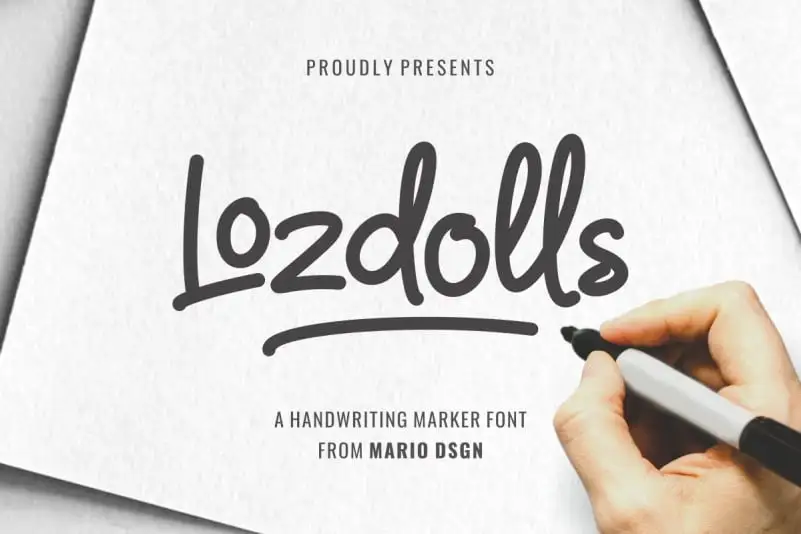
Lozdolls Handwritten Font – Download Grátis
Lozdolls Handwritten Font é uma elegante escolha para aqueles que buscam uma fonte escrita a mão com linhas limpas e personalidade forte. Ideal tanto para projetos criativos como logotipos, identidades visuais, convites, cartazes, design de mídias sociais, etiquetas e embalagens, essa fonte se destaca por sua graça e versatilidade. Ela não apenas brilha em letras minúsculas ou maiúsculas, mas também oferece ligaturas, alternâncias estilizadas, swashes e suporte a múltiplos idiomas. Além de ser perfeita para qualquer projeto visual que busque um toque único e sofisticado, essa fonte é uma ótima opção para quem deseja dar vida a seus projetos em design gráfico.